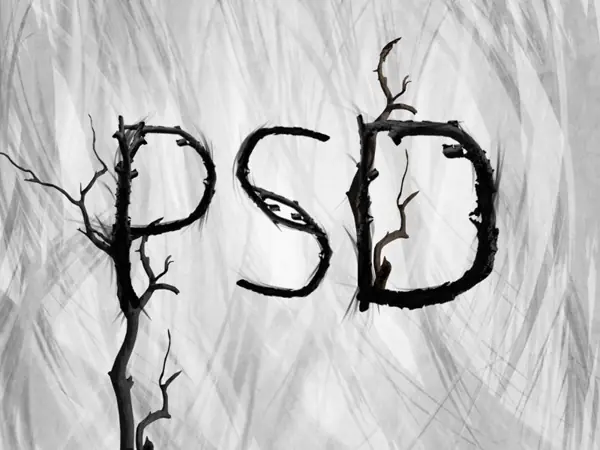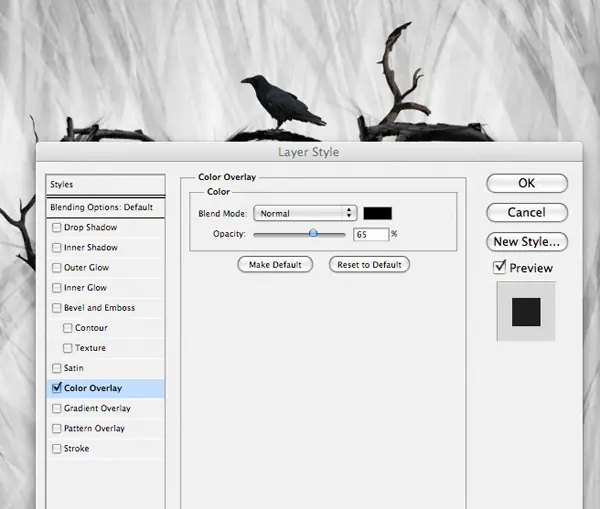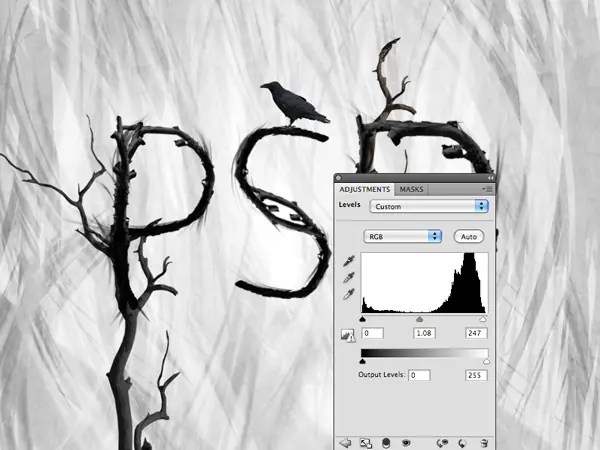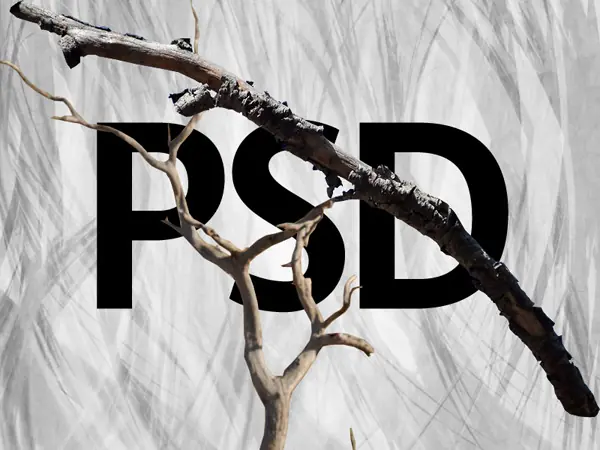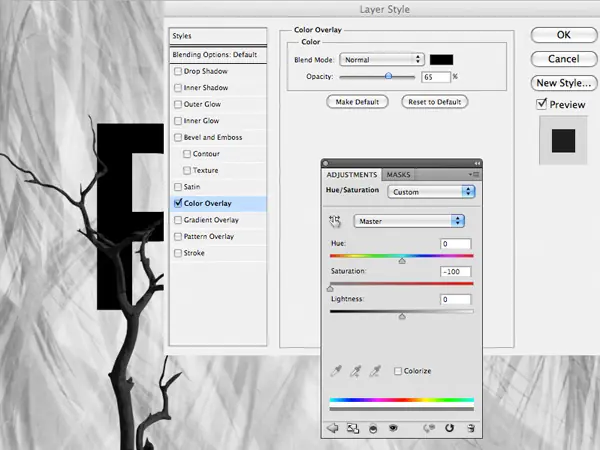
Imagen Final
Como siempre, esta es la imagen final que vamos a crear:
Paso 1
Crear un nuevo documento (800x600px).
Arrastra un degradado radial desde f8f8f8 de e0e0e0 en su capa de fondo:
Paso 2
Pegar en la textura de la corteza:
Ahora aplica un color / capa de ajuste de la saturación. Asegúrese de aplicar una máscara de recorte (Capa> Crear máscara de recorte), de modo que la capa de ajuste sólo afecta la capa de la corteza subyacente.
Ahora regresa a su capa de textura de la corteza. Reducir la opacidad al 30%, y cambiar su modo de mezcla a "superposición".
Paso 3
Ahora descargar el cepillo de las luces abstracta conjunto de los recursos necesarios para este tutorial.
Crear una nueva capa llamada "1 de las marcas de pincel.
Aplicar varias de las marcas de pincel (con un pincel negro). A continuación, cambie el modo de esta capa de mezcla a "superposición" y reducir la opacidad al 80%.
Paso 4
Ahora se aplican capas de un par más, la aplicación de las marcas de pincel más negro, y luego algunos los blancos. La idea es sólo a la capa de tu efecto de fondo:
Paso 5
Ahora aplica un poco de texto en el centro de su tela. El texto se puede decir lo que quieras, pero en este caso que acabo de escribir a máquina de los PSD de las letras. La fuente no es importante, pero es más fácil si se utiliza un tipo de letra legible, en negrita:
Paso 6
Ahora recortar y pegar en sus ramas de las fotos de sucursales en los recursos para este tutorial. Mantenga estas imágenes en capas separadas, de modo que usted puede fácilmente pegarlos en las capas posteriores:
Paso 7
Copia y pega tu foto del árbol en la parte inferior izquierda de la tela, colocándola en contra de la parte inferior de la letra P.
Ahora queremos hacer de nuestro árbol más estilizado para que encajen con nuestra composición general. Aplicar una capa de color opción de fusión de la capa de árbol, y luego aplicar un tono / saturación de la capa de ajuste (asegurándose de aplicar una máscara de recorte a la misma).
Superposición de colores de mezcla Opción Marco:
Modo de fusión: Normal
Color: 000000
Opacidad: 65%
Tono / Saturación capa de ajuste de configuración:
Hue: 0
Saturación: -100
Luminosidad: 0
Paso 8
Ahora queremos empezar a morphing nuestras imágenes de sucursales para ajustarse a nuestras cartas. Para ello vamos a utilizar la herramienta Puppet Warp. Coloque la rama más o menos por encima de su carta, y luego ir a editar urdimbre> títere. Urdimbre de la rama para caber alrededor de una parte de su carta:
Paso 9
Así es como su composición se ve una vez que haya deformado varias ramas para cubrir todas sus letras. Con cada capa de la rama, asegúrese de aplicar la misma superposición de color y la opción de fusión Tono / saturación de la capa de ajuste como la capa de la rama original.
Aquí está la composición de la capa de texto original oculta:
Paso 10
Ahora crearemos una nueva capa llamada "las marcas de pincel sobre las letras". Seleccione su cepillo de marcas abstractas de nuevo, y aplicar sus pinceles sobre sus cartas, la aplicación de un efecto sutil borde desgastado:
Paso 11
Un consejo rápido al aplicar los pinceles es la rotación de sus marcas de pincel cuando sea necesario. Juegos de cepillo puede no ser siempre en el ángulo correcto a seguir los contornos de las capas, de esta manera puede alterar el ángulo de sus pinceles para que encajen. Basta con abrir el panel de pinceles, y cambiar la opción de ángulo (ver más abajo):
Paso 12
Ahora crearemos una nueva capa llamada 'highlights'.
Arrastra varios gradientes radiales blanco a transparente sobre las copas de sus cartas.
A continuación, cambie el modo de esta capa de mezcla a "superposición" y reducir la opacidad al 40%.
Paso 13
Ahora pega en la foto cuervo de los recursos para este tutorial.
Coloque en la parte superior de una de sus cartas, y luego aplicar una superposición de colores opción de fusión:
Superposición de color Ajustes de mezcla de opciones:
Modo de fusión: Normal
Color: 000000
Opacidad: 65%.
Paso 14
Ahora aplicar una capa final de los niveles de ajuste para añadir contraste adicional a su composición.
Configuración de los niveles de ajuste de capa:
0 / 1,08 / 247